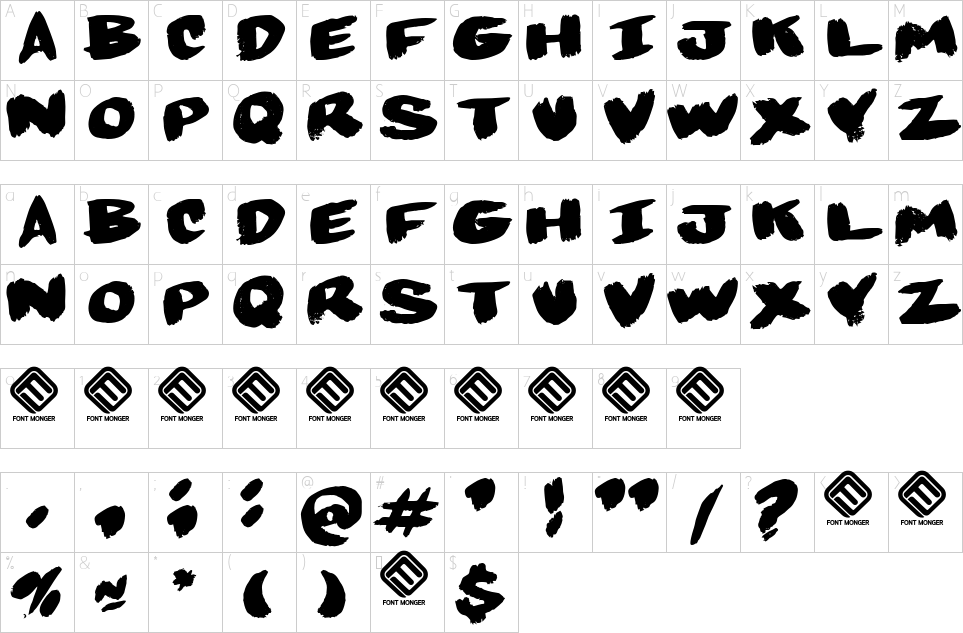
A Grandiose Font oferece uma experiência visual única para quem busca texturas fortes e elegantes. Desenvolvida por Font Monger, essa fonte vem à plataforma com 1001 opções de caracteres, garantindo variedade e originalidade em qualquer projeto gráfico que você desenvolver. Com um design moderno e sofisticado, ela é ideal para criar ambientes visuais impactantes, seja na tipografia corporativa ou nas seções destacadas de sites web. A fonte foi baixada 2872 vezes desde seu lançamento, evidenciando sua relevância e popularidade entre designers e criadores de conteúdo. Instale-a em seus projetos para explorar suas capacidades únicas e transforme qualquer texto em uma obra de arte visualmente impactante.